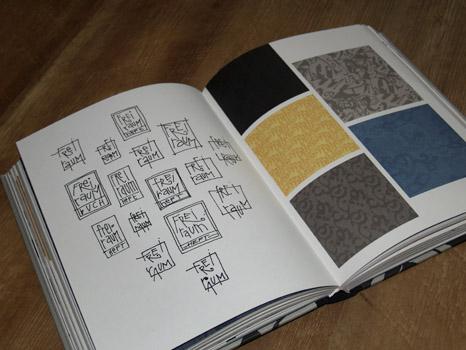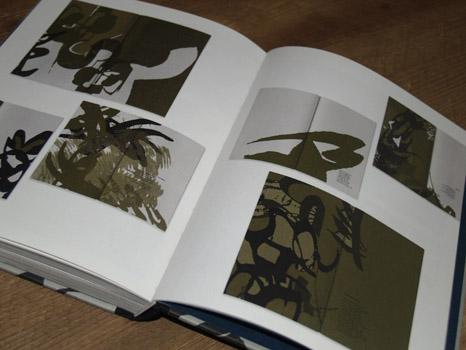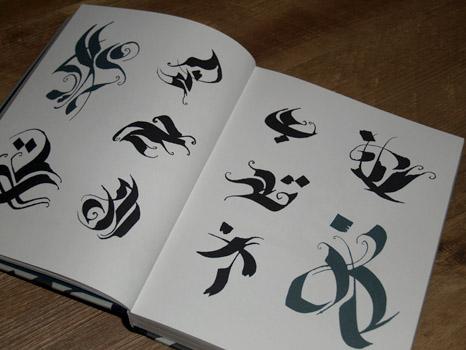
»TINTENTANZ ist kalligrafischer Ausdruckstanz, ist Jazz für die Hand, die schreibt.«* Erstmalig wird hier das Konzept der Schriftkurse von Hans-Jürgen Willuhn , das Generationen von Studierenden der FH Potsdam begeisterte, in Buchform vorgestellt. Es geht dabei nicht um das exakte Nachahmen von historischen Alphabeten, wie man es aus vielen anderen Büchern zum Thema Kalligrafie kennt; vielmehr wollen die Autoren Mut machen mit der eigenen Handschrift zu spielen und auch das Unperfekte zuzulassen.
Nach einer Einführung durch ein Gespräch mit der Verlegerin Karin Schmidt-Friderichs werden die Werkzeuge vorgestellt und Tipps zum Arbeiten gegeben. 500 farbige Abbildungen zeigen Ergebnisse der Kursteilnehmer, die die Bandbreite dieser Herangehensweise darstellen.
Außerdem geben die Autoren buchbinderische Anleitungen zur Präsentation der Arbeiten.
Der Titel, die Aufmachung und das einführende Gespräch versprechen einiges, was von diesem Buch zu erwarten ist. Man merkt gleich, dass man sich nach diesem Konzept ausprobieren und ausleben kann. Klecksen ist erlaubt und fast sogar gewünscht. Das macht Mut, gerade wenn man in sich selber nicht das Talent zum exakten, schönen Kalligrafieren vermutet.
Dennoch, oder gerade deswegen, frage ich mich für wen dieses Buch gedacht ist. Interessierte Kalligrafie-Anfänger haben diese Schwellenangst bereits überwunden und wollen sich an das exakte Schreiben wagen, ambitionierten, erfahrenen Schreibern sind die gezeigten Studentenarbeiten eventuell teilweise zu simpel. Einerseits werden Werkzeuge vorgestellt, die jeder geübte Kalligraf bereits kennen sollte, andererseits wird ein gewisses bewusstes Verständnis für Formen und Ästhetik vorausgesetzt. Ich habe ein bisschen den Eindruck, dass es sich in erster Linie an Willuhn-Alumni richtet, die damit ein Erinnerungsstück an die Kurse an der FH Potsdam haben.
Ein weiterer Kritikpunkt sind die sehr kurzen Anleitungen zu den Schriftübungen – statt dessen findet man seitenweisen mehr oder weniger ähnliche Arbeitbeispiele. Bei einem Großteil der Anleitungen geht es um das Binden und rechnergestützte Bearbeiten und Ergänzen der Ergebnisse. Das habe ich, zumindest in dem Umfang, nicht von diesem Buch erwartet.
Über das Konzept wird viel geschrieben, aber eine griffige Erklärung, wie dieses genau aussieht sucht man vergeblich.
Trotz dieser m. E. deutlichen Schwächen ist der Band auf Grund der aufwendigen (vom Hermann-Schmidt-Verlag gewohnten) Ausstattung und der vereinzelten inspirierenden Beispiele für interessierte Schreiber dennoch durchaus empfehlenswert und sollte in keiner kalligrafischen Bibliothek fehlen – auch wenn er bei genauer Betrachtung mehr Erwartungen weckt als er erfüllt.
Für Anfänger, die in die Kalligrafie einsteigen wollen ist das Buch nichts, da doch ganz wesentliche Basics fehlen. Aber das wird ja auch deutlich gesagt: »Wenn Sie Kalligrafie im Sinne von Schönschrift lernen wollen und klassische ›Ballett-Etüden‹ für die Feder suchen, dann legen Sie dieses Buch am besten schnell aus der Hand«*